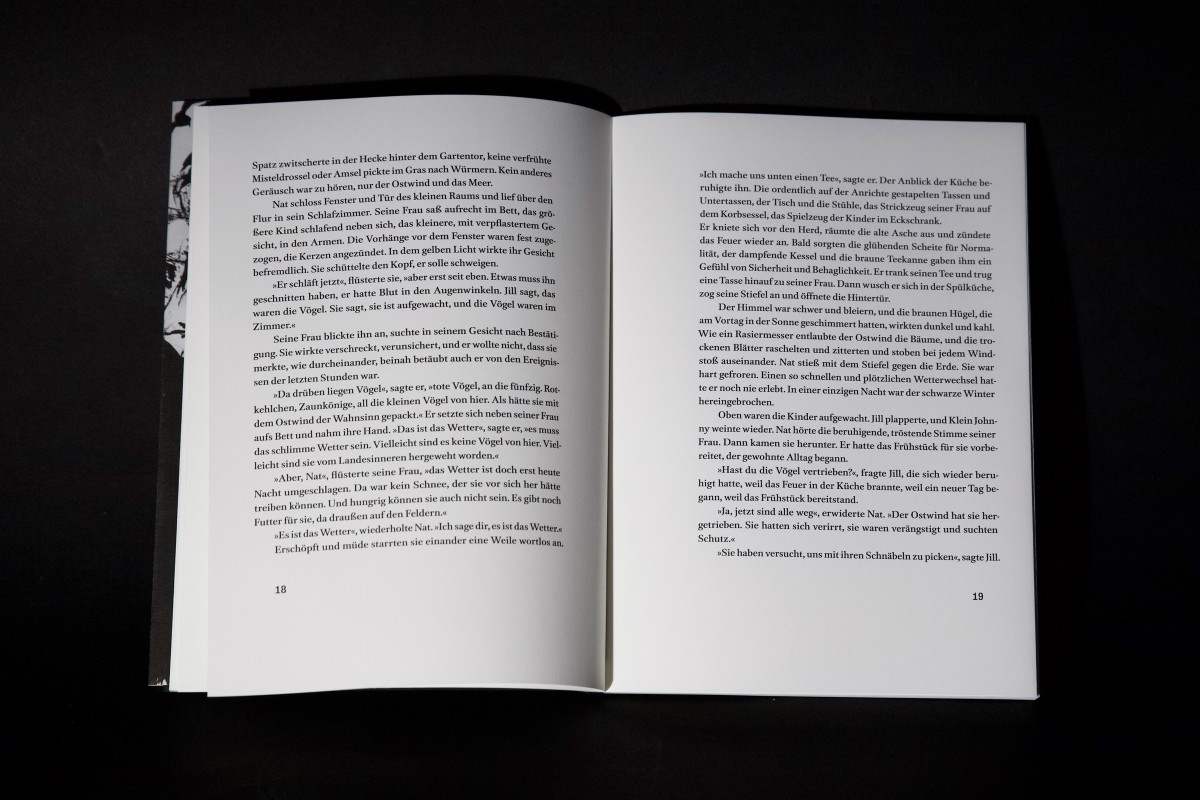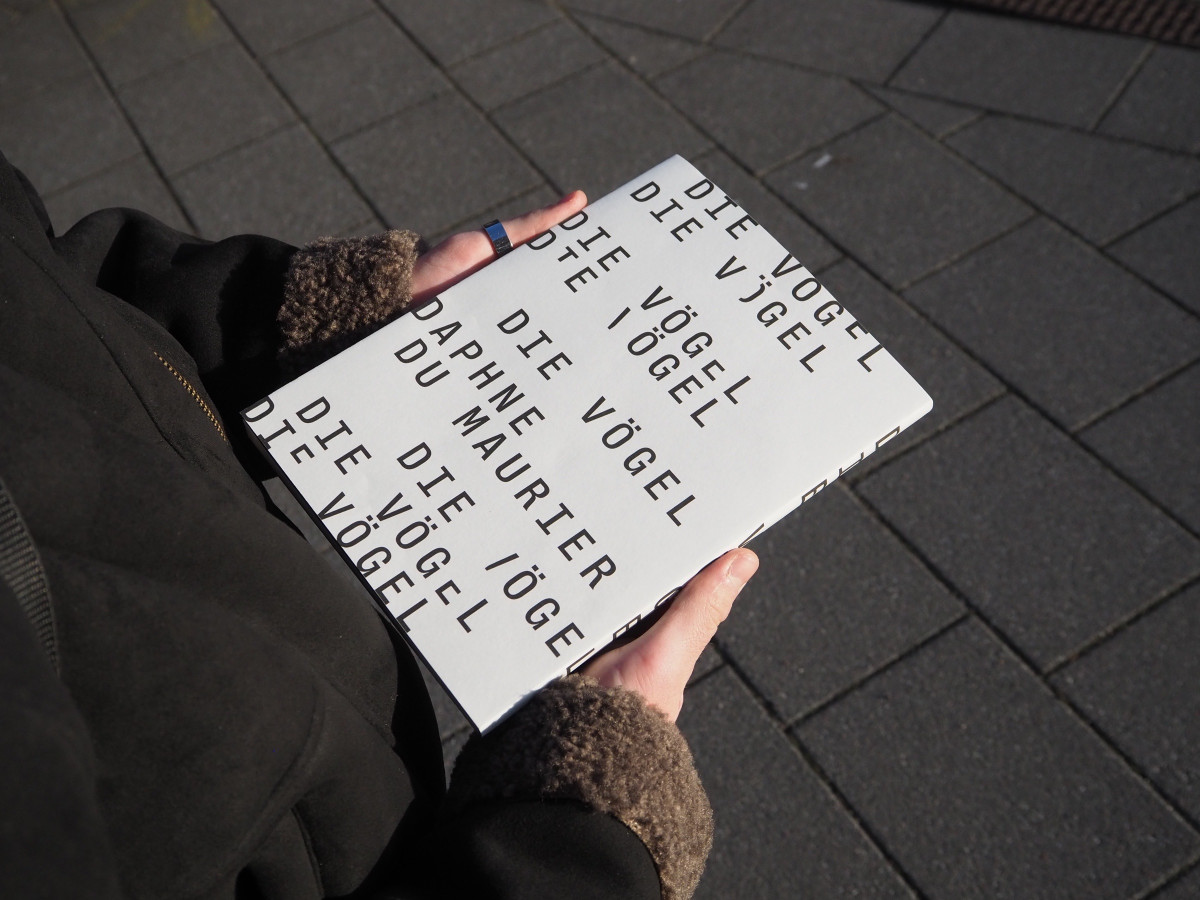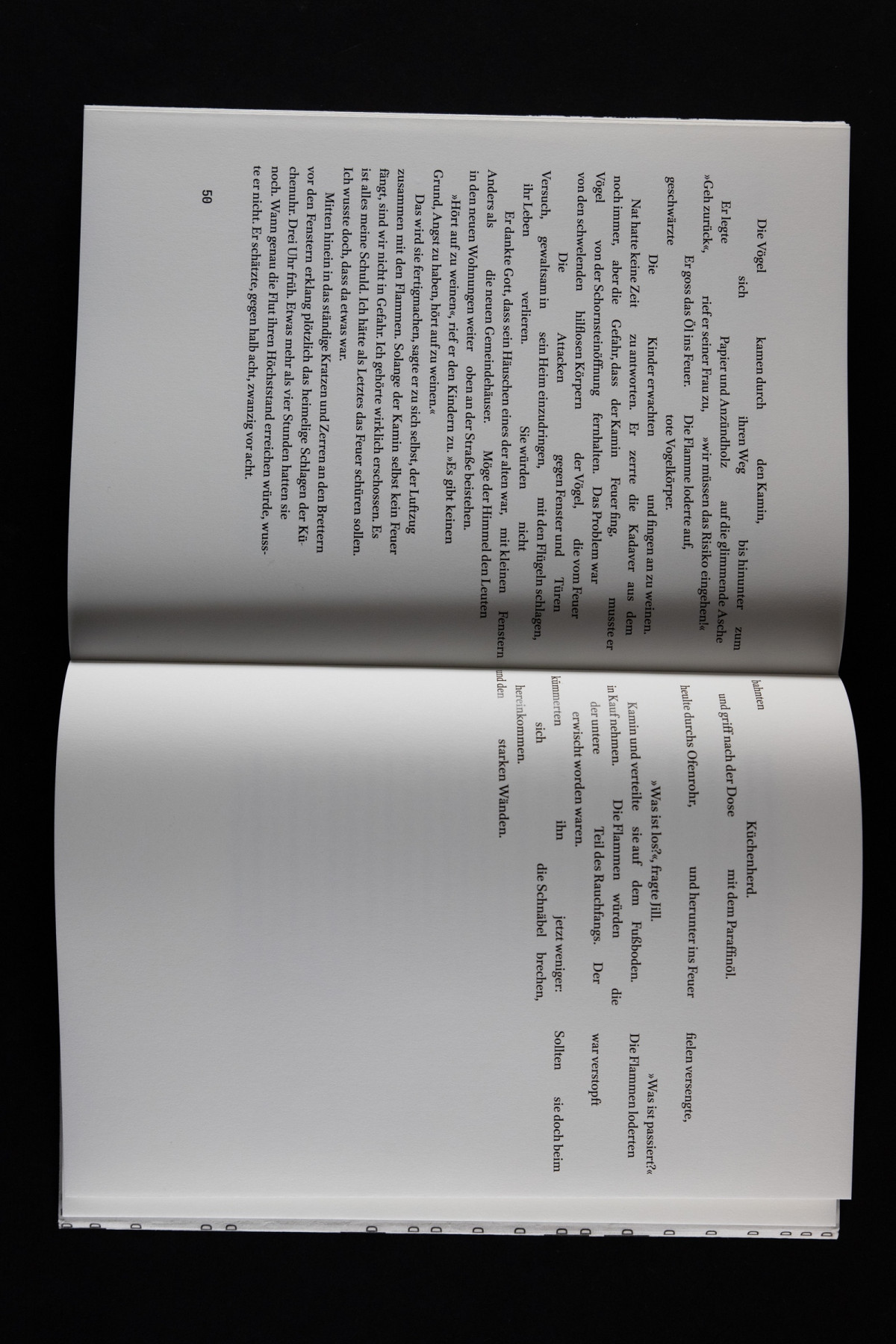
Die Neugestaltung der Novelle „Die Vögel“ von Daphne du Maurier, welche von einer rätselhaften, zunehmend bedrohlichen Angriffswelle durch Vögel auf die Menschheit erzählt, thematisiert den Einbruch des Chaos in eine scheinbar geordnete Welt. Im Zentrum steht nicht die bildliche Darstellung der Vögel, sondern das Erzeugen von Unruhe und Bedrohung durch typografische Mittel. Der Text wird gestört: Wörter lösen sich aus dem Satzspiegel, Lücken reißen auf, der Blocksatz beginnt zu „flattern“. Diese typografischen Eingriffe steigern sich parallel zur Handlung und spiegeln die zunehmende Eskalation wider. Ergänzt wird die Gestaltung durch monochrome Illustrationen, die wie ein Vorspann in die Geschichte einführen – und die Plötzlichkeit der Bedrohung spürbar machen.
So entsteht ein Buchobjekt, das nicht nur gelesen, sondern körperlich erfahren werden kann – als gestalterische Übersetzung einer literarischen Atmosphäre der Unsicherheit und Kontrolle.
The redesign of Daphne du Maurier’s novella The Birds, which tells the story of a mysterious and increasingly threatening wave of bird attacks on humanity, explores the intrusion of chaos into an apparently ordered world. The focus lies not on visual depictions of the birds themselves, but on evoking a sense of unrest and menace through typographic means. The text is disrupted: words break away from the text block, gaps open up, the justified alignment begins to “flutter.” These typographic interventions intensify alongside the narrative, reflecting its escalating tension. The design is complemented by monochrome illustrations that act like a prologue to the story—making the suddenness of the threat tangible.
The result is a book object that is not only read, but physically experienced—an interpretive translation of literary atmosphere into visual form, shaped by uncertainty and loss of control.